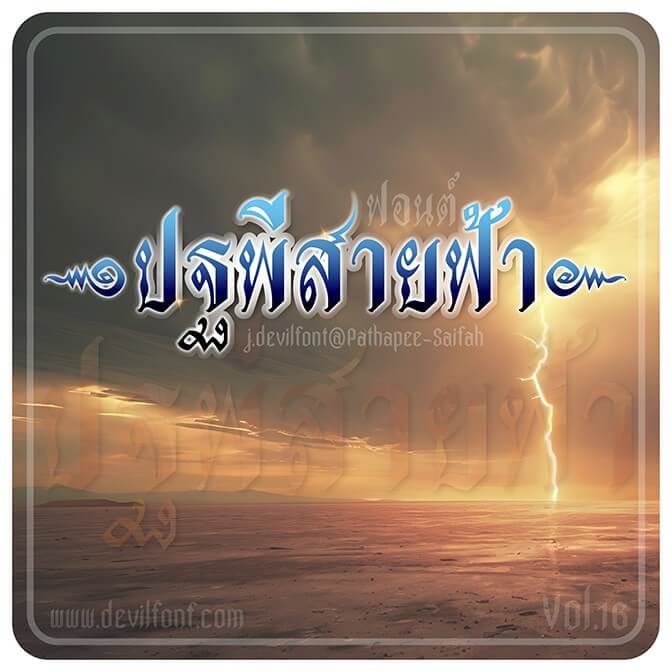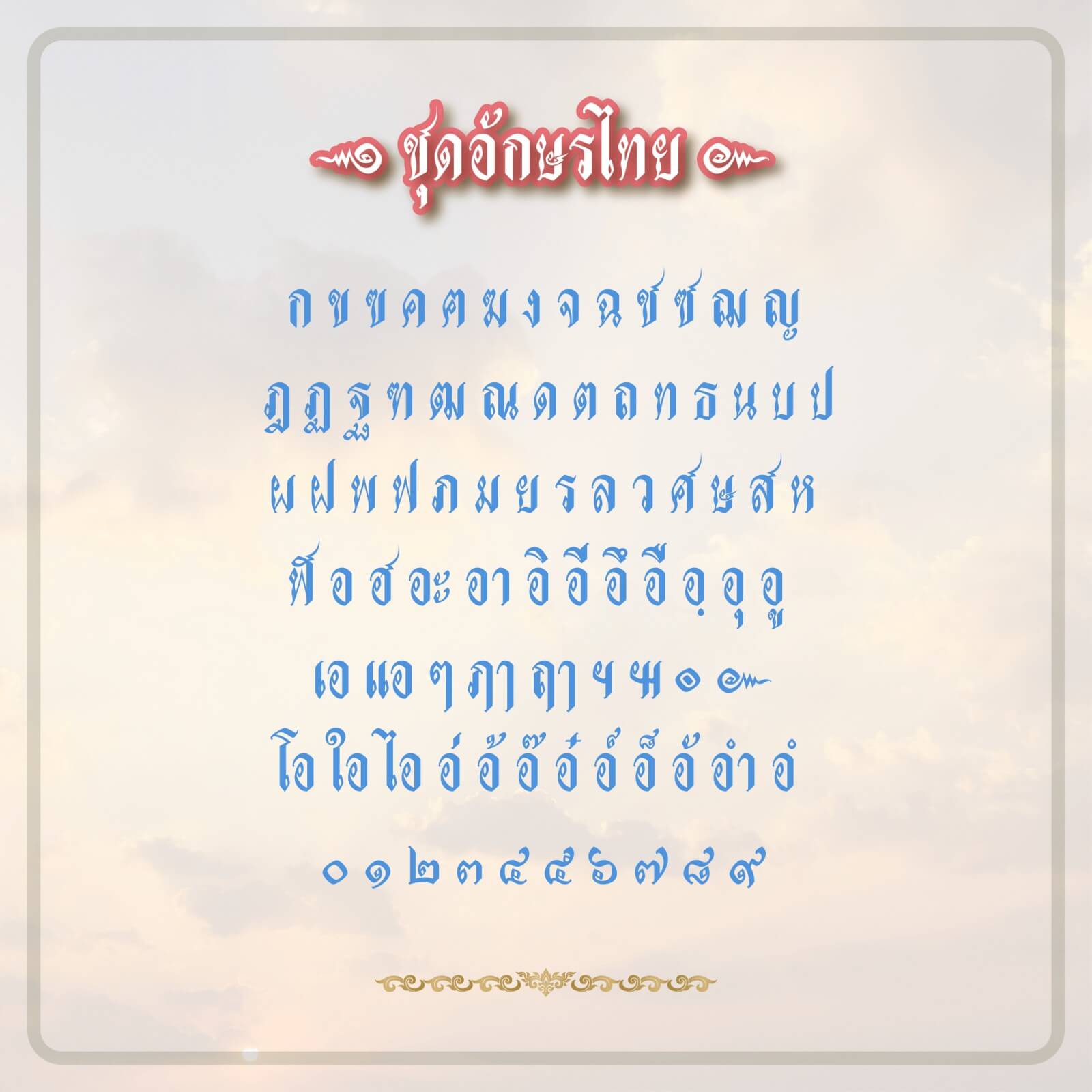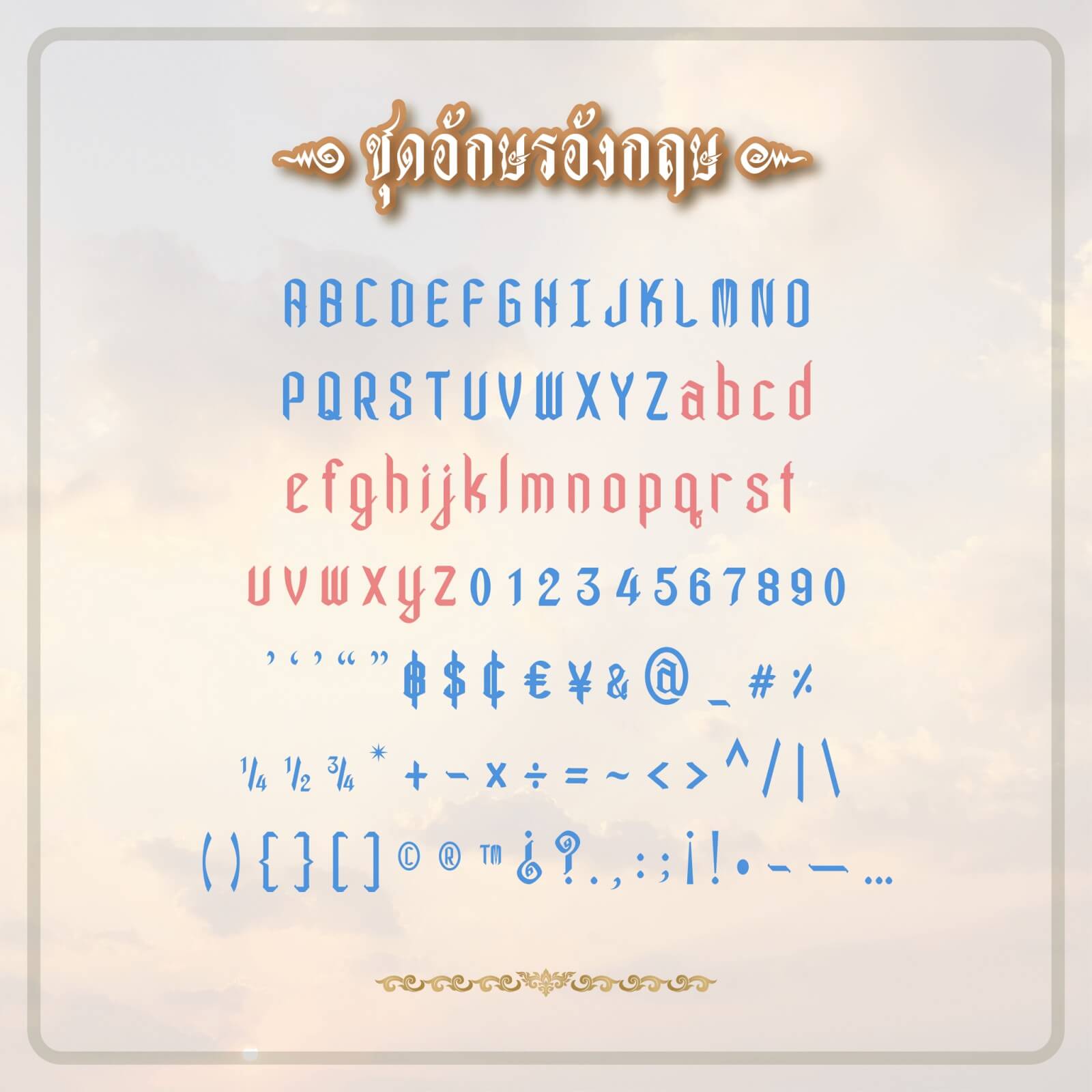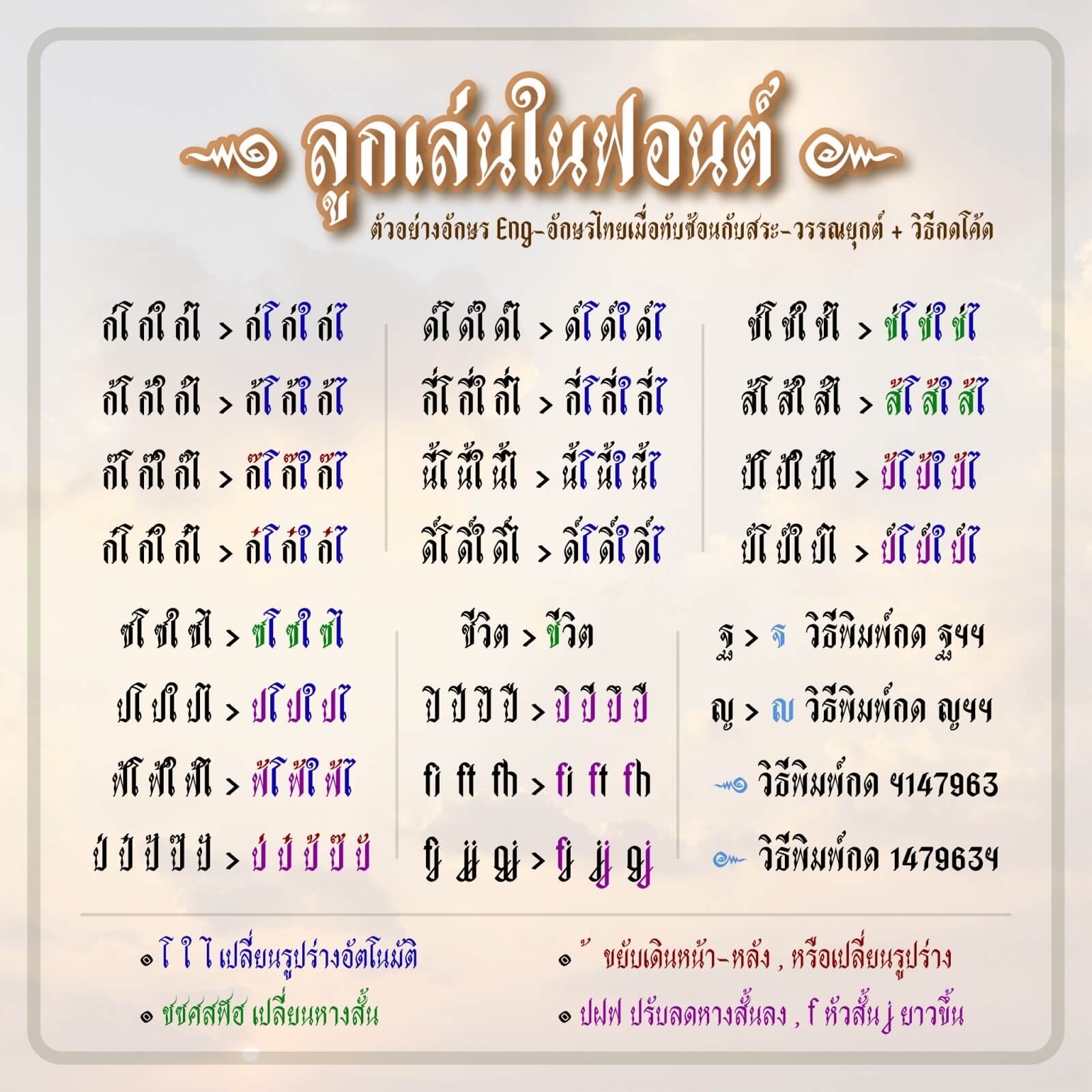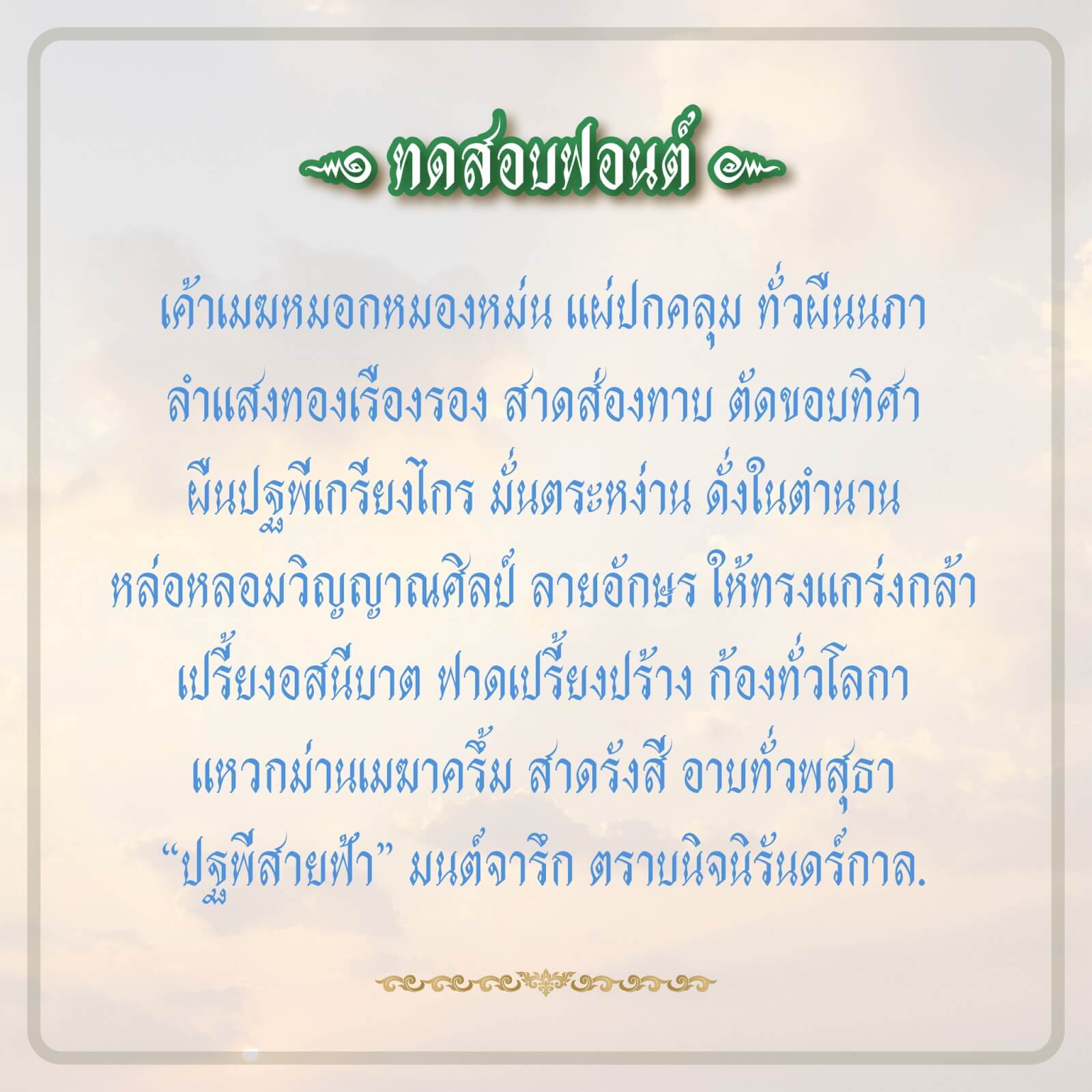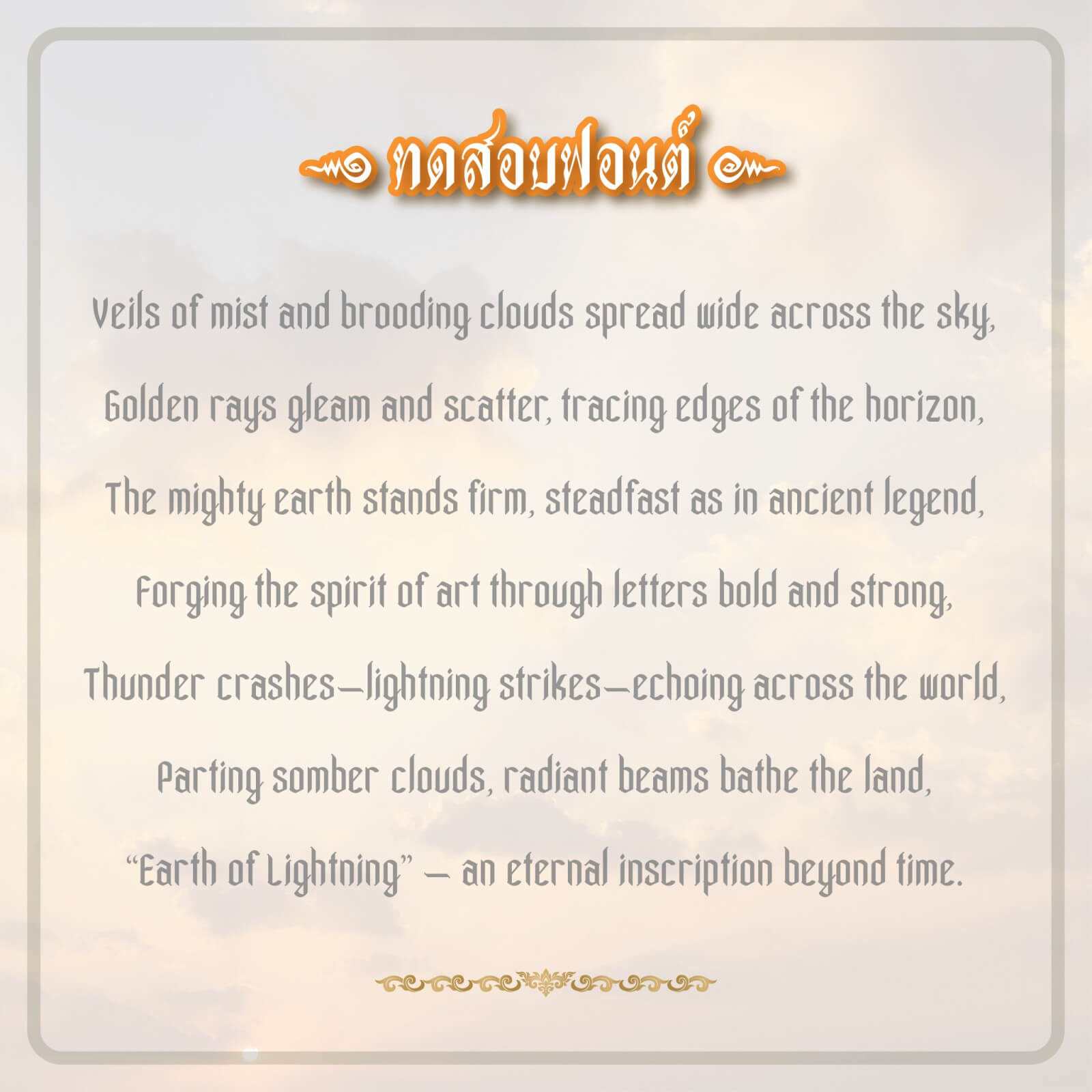
ฟอนต์ ปฐพีสายฟ้า ผลงานฟอนต์ชุดที่ 16 – ลักษณะฟอนต์ไทย พาดหัว งานป้าย งานไม้ งาน cnc บทกลอน ป้ายร้านค้า สายมู ปกนวนิยาย นิตยสาร เทศกาล ศาลเจ้า ของโบราณ โลโก้ สกรีนเสื้อ แสดงงานพิธี สารคดี สื่อโฆษณา แบรนด์สินค้า ความเป็นเอกลักษณ์ไทยโบราณร่วมสมัย
รายละเอียด ฟอนต์ปฐพีสายฟ้า
- ใช้งานด้วย kerning ปรับระยะห่างของชุดอักษรทั้งไทย-อังกฤษ
- ใช้ mark ในการจัด อักษร+สระ+วรรณยุกต์ เพิ่มการไล่ระดับสระ+วรรณยุกต์ อัตโนมัติ
- เพิ่มลูกเล่นที่ โ ใ ไ ที่ยืด-หด และเปลี่ยนรูปในเวลาพิมพ์อัตโนมัติ
- ตัวอักษรมีหาปรับหางสั้นเองเมื่อพิมพ์ สระอิ อี อึ อื ่ ้ ๊ ๋ ์ ็ ั ํ
- ตัวอักษรมีหางปรับหางสั้นเองเมื่อพิมพ์ตัวที่คำตัวอักษรที่มีหาง เช่น สี่ปี หาง ส จะไม่ทับกับสระอีบน ป / ป่ป้ป๊ป๋ เปลี่ยนรูปทรง
- เพิ่มวิธีการพิมพ์ โคมูตร ( ๛ ) กด ฯ147963 ต้องการโคมูตรตัวพิเศษกลับด้าน 147963ฯ
- เพิ่มวิธีการพิมพ์ตัวบาลี ญ ฐ แบบไม่มีเชิง ด้วยการกด ญฯฯ / ฐฯฯ จะได้ตัวที่ไม่มีเชิง
- ตัวอักษรอังกฤษ ก็มีการปรับค่าแก้โค้ดให้ไม่มีหางทับกัน แบบ auto
- ปล. ยังมีลูกเล่นซ่อนอยู่อีก …ฯลฯ แต่ส่วนใหญ่จะเป็นการปรับอัตโนมัติแล้ว